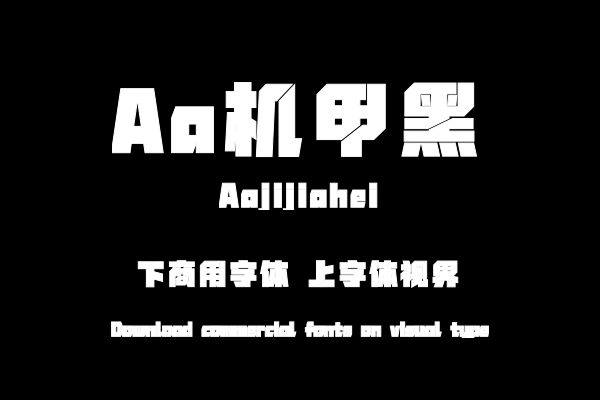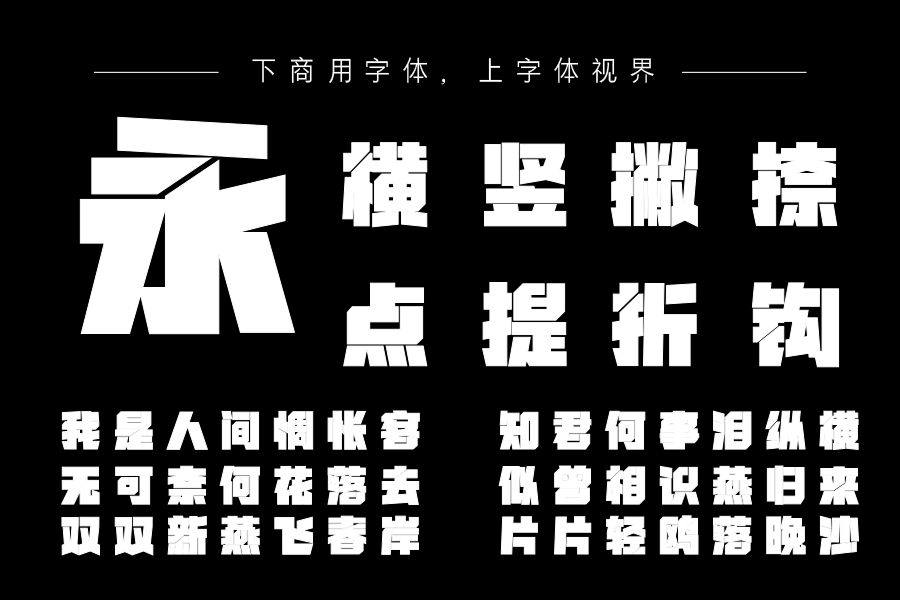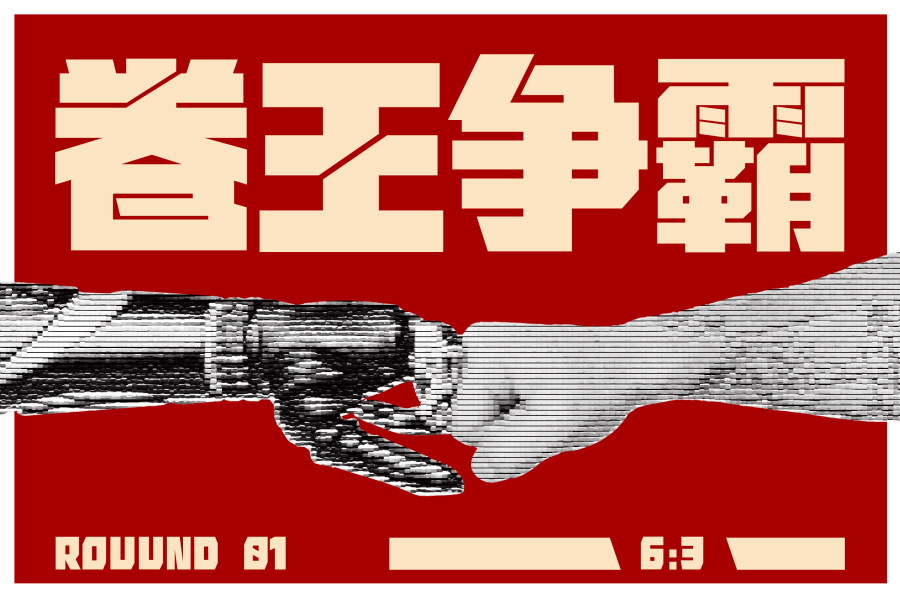
以简单斜切的笔画和方正饱满的结构体现机械冷静却充满力量的科技感,通过斜切的白空间表现机械结构间的叠压拼合,迎合用户对于极粗字体的使用需求。购买须知:“下载服务费”与“字体VIP”所获得字体 仅用于个人非商用, 商用请联系付费授权。本字体为电脑用字,手机没有root权限不支持直接手机换字(手机如何root,请自行百度搜索教程)。购买前请先 了解清楚后再付款 ,字体为虚拟产品无法回收 一旦购买不支持退款。